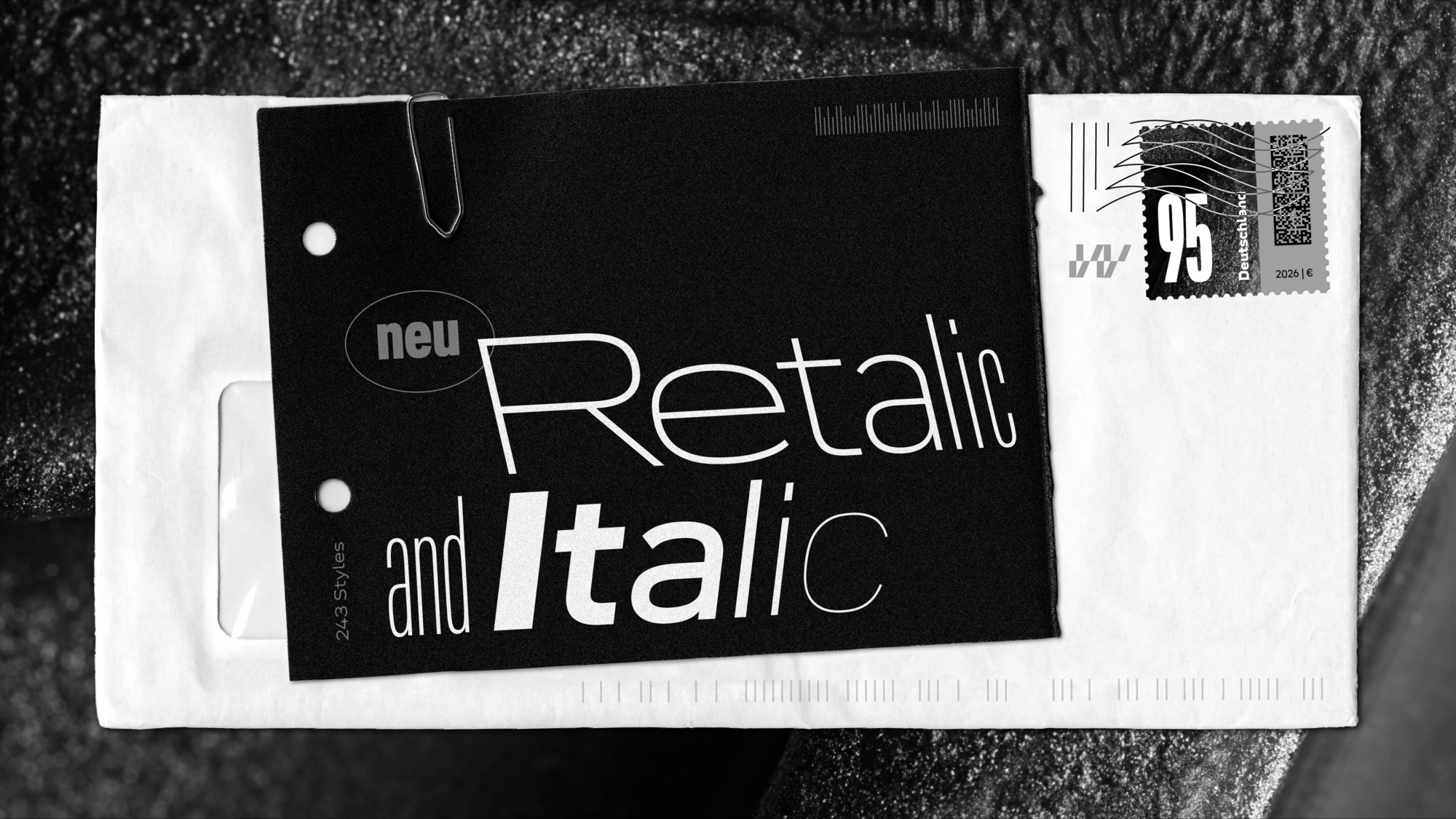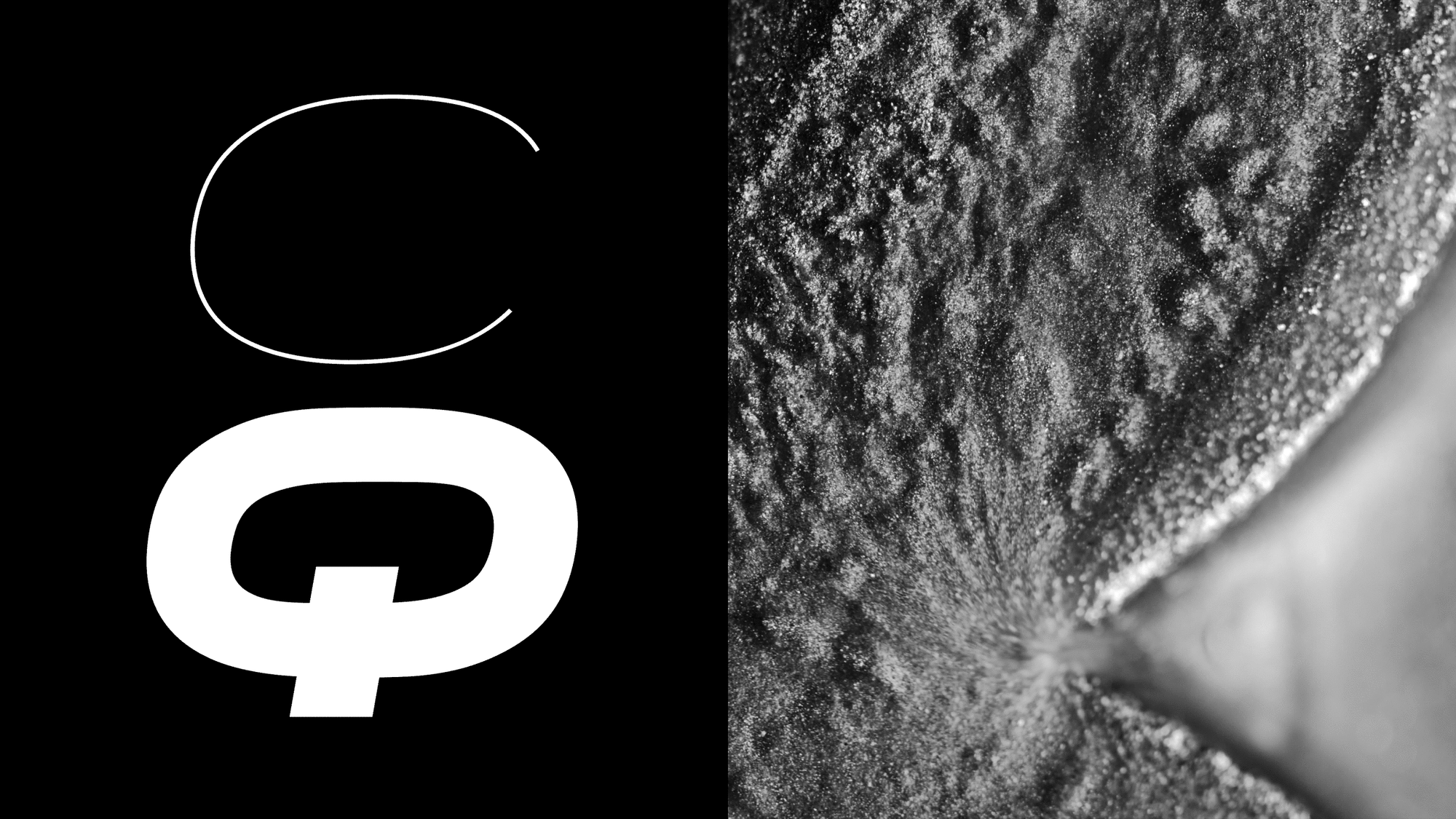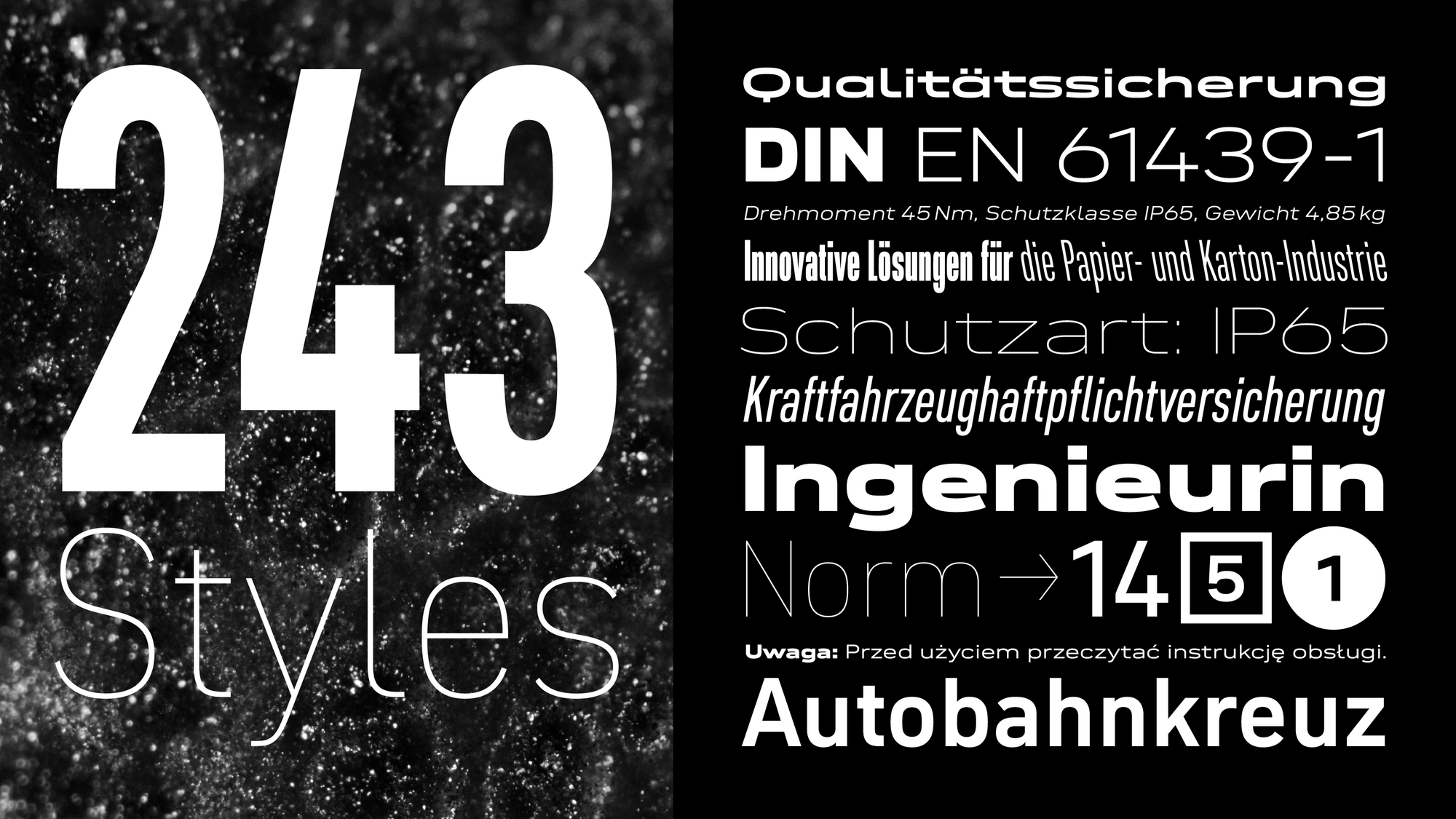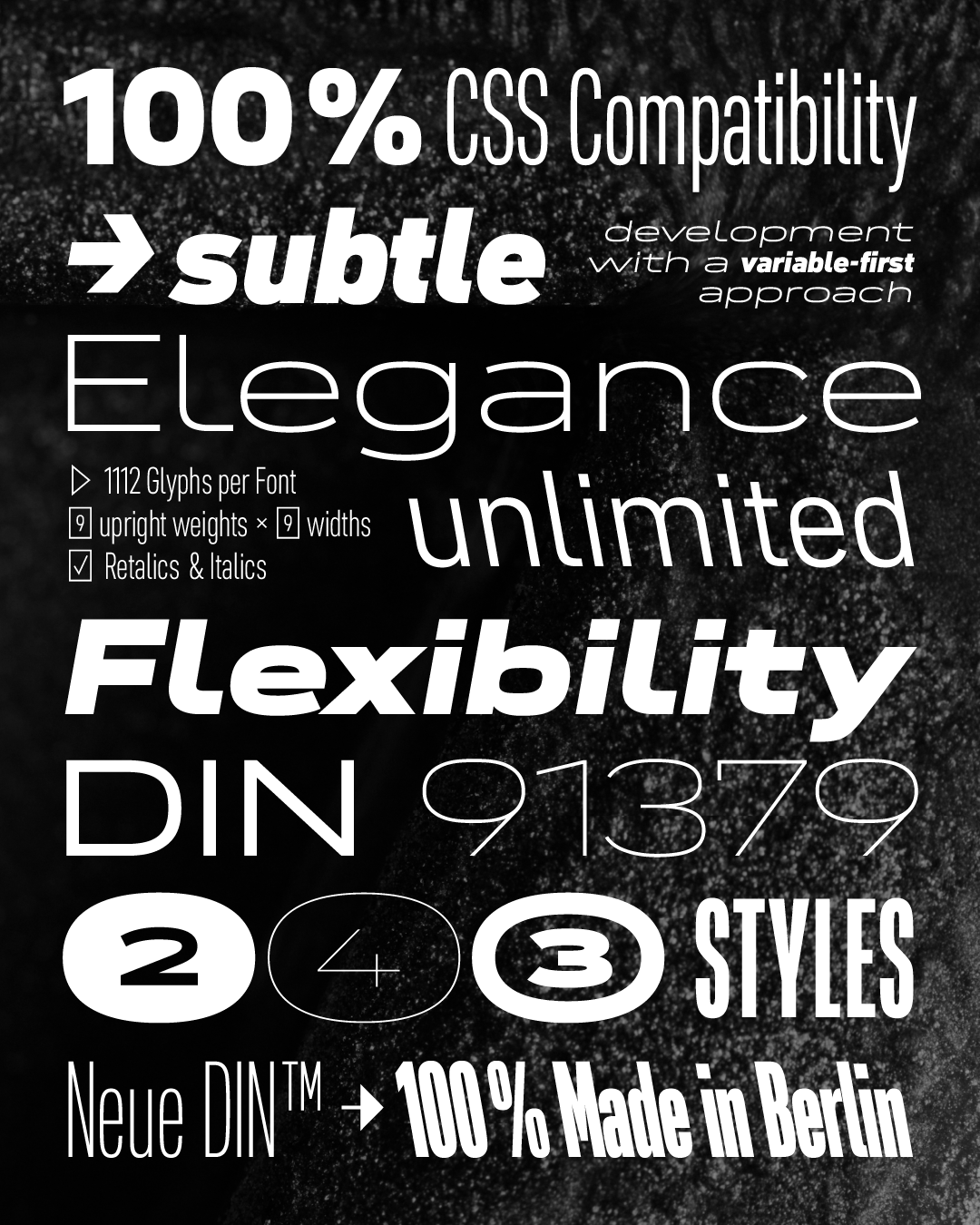
Die Neue DIN wurde von Jan Hendrik Weber, Andreas Frohloff und Olli Meier gestaltet und erschien 2023 bei Fontwerk. Die Schrift basiert auf der DIN 1451. Durch die Umsetzung als variabler Font konnte ein besonders großer Gestaltungsraum der Schnitte aufgespannt werden. Die Schrift ist in neun Strichstärken und neun Weiten verfügbar, zusammen also 81 Fonts mit erweiterter lateinischer Belegung. Alternativ steht der variable Font zur Verfügung, der den gesamten Gestaltungsraum in einem Font vereint. Seit September 2025 gibt es für alle Aufrechten passende Kursive und Links-Kursive (›Retalic‹), so dass sich der Umfang der statischen Fonts auf 243 erhöht.